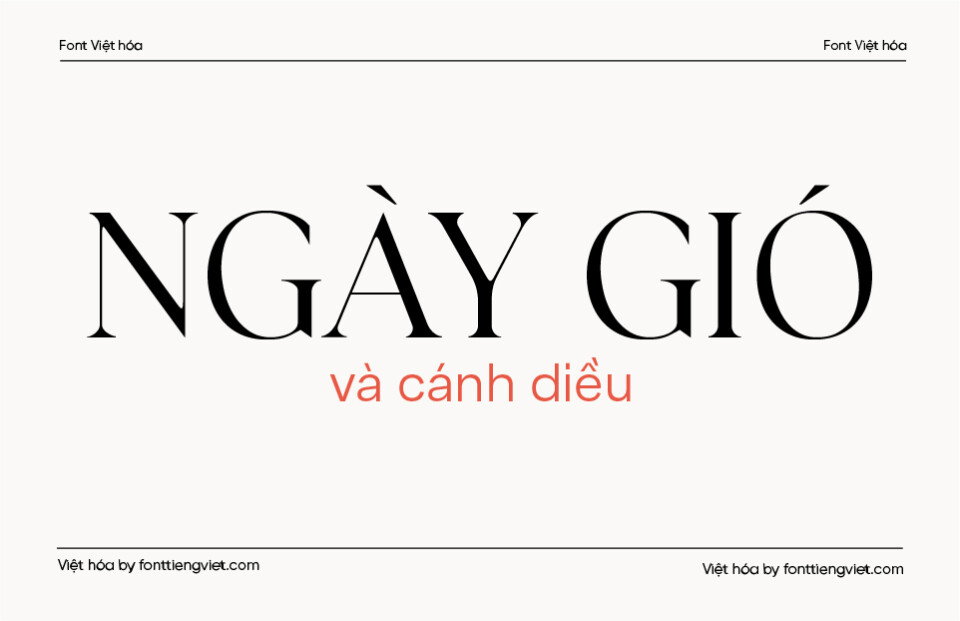
Tải Font Việt hóa 1FTV VIP Mollie Glaston Miễn Phí Cho Thiết Kế Sang Trọng Giới thiệu về Font Việt hóa 1FTV VIP Mollie Glaston Trong thế giới thiết kế đồ họa hiện đại, việc lựa chọn một bộ Font Miễn Phí chất lượng luôn là ưu tiên hàng đầu của các nhà sáng tạo. Font Việt hóa 1FTV VIP Mollie Glaston nổi lên như một hiện tượng nhờ sự kết hợp hoàn hảo giữa nét cổ điển serif và sự thanh thoát của phong cách hiện đại. Đây là bộ font chữ đặc biệt được tinh chỉnh kỹ lưỡng để phù hợp với bảng mã tiếng Việt, giúp người dùng không còn lo lắng về lỗi hiển thị dấu hay khoảng cách chữ không đều. Với cấu trúc chữ thanh mảnh nhưng đầy quyền lực, Mollie Glaston mang đến một luồng gió mới cho các ấn phẩm truyền thông tại Việt Nam. Đặc điểm nổi bật của Font Việt hóa 1FTV VIP Mollie Glaston Thiết kế Serif tinh tế và đẳng cấp Điểm ấn tượng nhất của Font Việt hóa 1FTV VIP Mollie Glaston chính là những đường chân chữ (serif) được gọt giũa sắc nét. Sự biến hóa giữa các nét thanh và nét đậm tạo nên một nhịp điệu thị giác lôi cuốn, giúp văn bản trở nên chuyên nghiệp và sang trọng hơn. Bộ font này không chỉ dừng lại ở các ký tự cơ bản mà còn đi kèm với nhiều ký tự thay thế (alternates) và các chữ ghép (ligatures) độc đáo. Điều này cho phép các bạn học sinh, sinh viên hay những người yêu thích thiết kế có thể thỏa sức sáng tạo ra những tiêu đề sách, bìa báo hay thiệp mời mang đậm dấu ấn cá nhân mà không cần thao tác thủ công phức tạp. Khả năng ứng dụng đa dạng trong thực tế Dù bạn đang thực hiện một dự án bài giảng điện tử cho nhà trường hay thiết kế bộ nhận diện thương hiệu cho một cửa hàng thời trang, Font Việt hóa 1FTV VIP Mollie Glaston luôn hoàn thành tốt nhiệm vụ của mình. Độ tương phản cao của chữ giúp người đọc dễ dàng tiếp nhận thông tin ngay cả ở kích thước nhỏ. Đặc biệt, font chữ này cực kỳ phù hợp cho các thiết kế in ấn như poster, catalogue, và các nội dung trang trí trên mạng xã hội. Sự mềm mại của các đường cong trong Mollie Glaston giúp cân bằng lại những bố cục góc cạnh, tạo nên một tổng thể hài hòa và thuận mắt cho người xem. Lợi ích khi sử dụng Font Việt hóa 1FTV VIP Mollie Glaston Tối ưu hóa quy trình thiết kế tiếng Việt Trước đây, nhiều người thường gặp khó khăn khi sử dụng các font chữ nước ngoài vì chúng không hỗ trợ các dấu thanh đặc thù của tiếng Việt như dấu hỏi, dấu ngã hay các chữ cái ươ, ăt. Tuy nhiên, với phiên bản Font Việt hóa 1FTV VIP Mollie Glaston, mọi rào cản về kỹ thuật đã được loại bỏ hoàn toàn. Các dấu tiếng Việt được thiết kế cân đối, không quá cao cũng không quá thấp so với thân chữ, đảm bảo tính thẩm mỹ cao nhất cho đoạn văn bản. Điều này đặc biệt có ý nghĩa đối với môi trường giáo dục, nơi yêu cầu sự chính xác và rõ ràng trong trình bày văn bản tiếng Việt chuẩn mực. Nâng tầm giá trị thẩm mỹ cho tác phẩm Việc sử dụng một font chữ “VIP” như Mollie Glaston giúp sản phẩm của bạn trông đắt tiền và có đầu tư hơn. Thay vì sử dụng những phông chữ mặc định nhàm chán, việc cài đặt và sử dụng bộ font này sẽ giúp các bài thuyết trình hay dự án sáng tạo của bạn nổi bật giữa đám đông. Đây là công cụ đắc lực để truyền tải thông điệp một cách tinh tế, thể hiện sự chỉn chu và gu thẩm mỹ tinh tế của người thực hiện. Kết luận về bộ Font Việt hóa 1FTV VIP Mollie Glaston Tóm lại, Font Việt hóa 1FTV VIP Mollie Glaston là một sự lựa chọn không thể bỏ qua đối với bất kỳ ai đang tìm kiếm sự khác biệt và đẳng cấp trong thiết kế. Với tính năng hỗ trợ tiếng Việt hoàn hảo và phong cách sang trọng, bộ font này chắc chắn sẽ làm hài lòng cả những người dùng khó tính nhất. Hãy nhanh tay tải về và trải nghiệm sức mạnh của những đường nét tinh tế mà bộ chữ này mang lại cho các dự án của bạn tại Font Miễn Phí, Font Việt Hóa, Font Việt hóa 1FTV VIP Mollie Glaston để nâng tầm sáng tạo ngay hôm nay.
Font Việt hóa 1FTV VIP Mollie Glaston